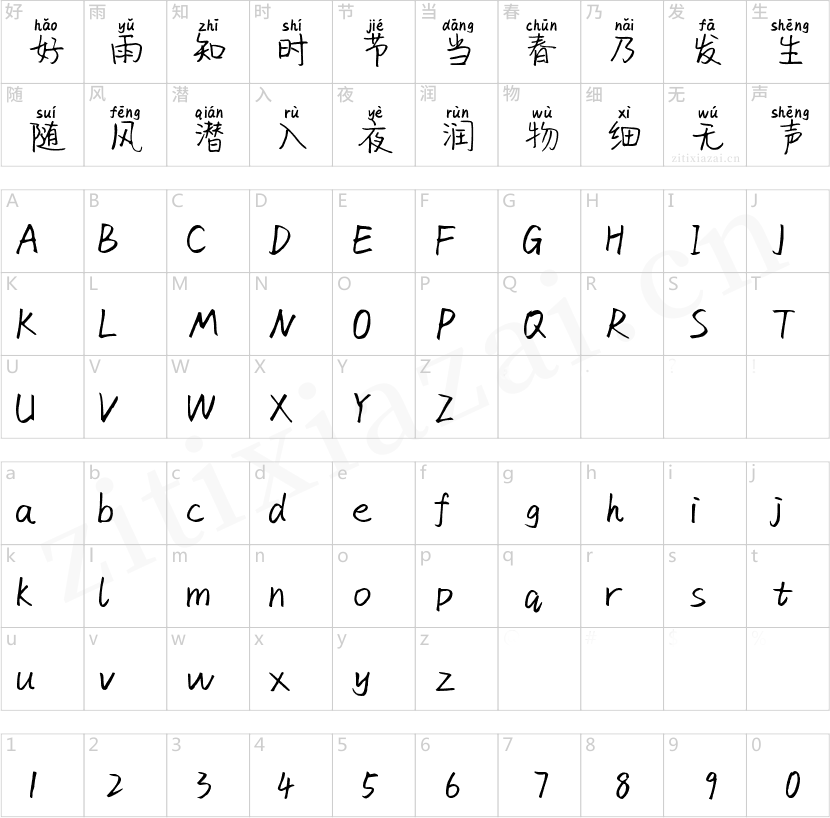
Aa进击的小奶狗
Aa进击的小奶狗,这款字体结构工整、笔画清晰,兼顾美观与易读性,适用于标题、正文、海报、包装、LOGO 等多种场景。字形优雅稳定,风格百搭耐看,适配日常排版与创意设计,让文字呈现更舒适、更具质感。Aa进击的小奶狗一笔一画,皆是细节,以均衡的比例、流畅的线条打造舒适视觉体验,字形端正大气,风格简约现代。无论是商业设计、品牌宣传还是日常排版,都能轻松驾驭,让文字更有格调与力量。Aa进击的小奶狗字体下载。
Aa进击的小奶狗是一款非常具有艺术性的字体,它的设计灵感来源于对古典艺术的研究,同时又融入了现代字体设计的元素。字形优美,笔画粗细变化自然,给人以大气、典雅的感觉。Aa进击的小奶狗是一款既传统又现代的字体,它的设计充满艺术感,美观大方,实用性也非常强。无论是对于设计师还是对于普通读者来说,都是一种非常不错的字体选择。Aa进击的小奶狗适合用于具有艺术感的场合,比如海报、宣传单张、书籍封面等。由于其字形流畅且具有动态感,也适合用于大量的文本排版,如报纸、杂志等。